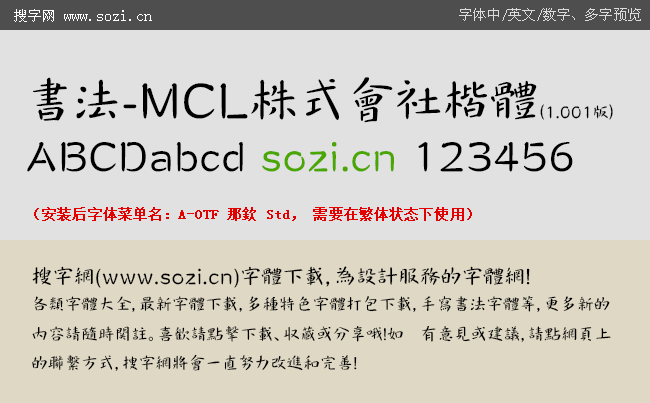
書法-MCL株式會(huì)社楷體
搜字網(wǎng)給大家提供一款很漂亮的書法字體下載。MCL株式會(huì)社楷體,這款字體是日系公司開發(fā)制作的一款楷體書法字體,這款楷體有別于常見的其他字庫(kù)的標(biāo)準(zhǔn)式楷體,手寫風(fēng)格極濃,非常適合古典畫冊(cè)、標(biāo)題等場(chǎng)合使用。